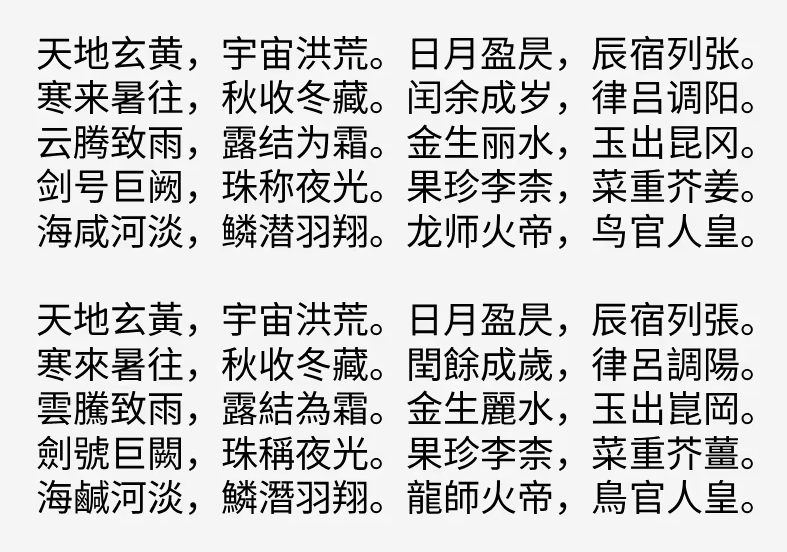
思源黑体由全球知名设计软件公司 Adobe 与互联网巨头 Google 联合开发,于2014年7月正式发布。是一款覆盖简体中文、繁体中文、日文、韩文的无衬线字体。
从 ExtraLight 到 Heavy,共7个字重级别,可以满足从正文排版到标题设计各个场景需求。而且单个字体文件包含超过 65000 个字形,覆盖 GB18030、Big5、JIS X 0208、KS X 1001 等主流字符集,甚至包含了生僻字、异体字和部分少数民族文字。
思源黑体保留了黑体的现代感与清晰度,在视觉与笔画粗细上高度协调,排版时不会出现突兀的感觉,能兼顾不同用户的阅读习惯,所以在制作海报、开发App、视频字幕中都有广泛的应用。甚至很多字体都是根据思源系列衍生而来。